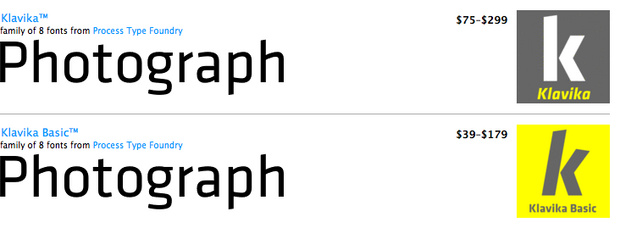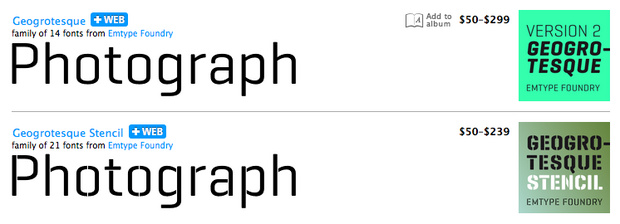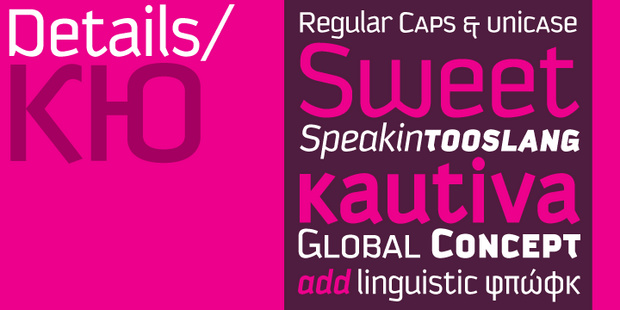
Suche Schrift für Logo (Fotograf)
ich bin absoluter Neuling auf diesem Gebiet und habe nun folgendes Vorhaben:
ich bin Fotograf und gestalte gerade mein corporate design...
Nun suche ich eine Schrift für mein logo, in der das "P" , also der Kopf des Buchstabens, eckig ist...
(so wie ein Diarahmen)...
vielleicht kommen ja noch ein paar...
aber die gefallen mir schon mal sehr gut, vielleicht noch nen ticken zu rundlich...
ich hoffe ich nerve nicht, aber das richtige war noch nicht dabei...
so in die Richtung: Bank Gothic Light ....
Mach halt einfach selbst mal einen Vorschlag, in welche Richtung es denn gehen soll. Sonst bleibt es stochern im Nebel.
ja, wie gesagt, so bank gothic light...
das P kantig und das o wie ein aufgestelltes Dia-Rähmchen...
ich hoffe ich nerve nicht, aber das richtige war noch nicht dabei...
so in die Richtung: Bank Gothic Light ....
Ein bisschen Eigeninitiative wäre nicht schlecht. Wie wäre es, wenn du Bank Gothic Light in die Suche der Seite eingeben würdest, die ich dir genannt habe. Dann kommst du vielleicht auf die gesuchte Schrift, da dir ja wohl etwas ganz bestimmtes vorschwebt. http://www.identifont.com/similar.html. Du kannst auch gerne auf der Linotype-Seite schauen, da gibt es auch einen Fontfinder.
das P kantig und das o wie ein aufgestelltes Dia-Rähmchen...
das A wie ein Stativ, das X wie ein Fototisch ... ;-)
Wenn es für ein Logo ist, warum dann nicht nach den eigenen präzisen Vorstellungen selbst zeichnen? Einen Font zu finden, der allen Anforderungen von Dir zu 100 Prozent gerecht wird, ist unwahrscheinlich.